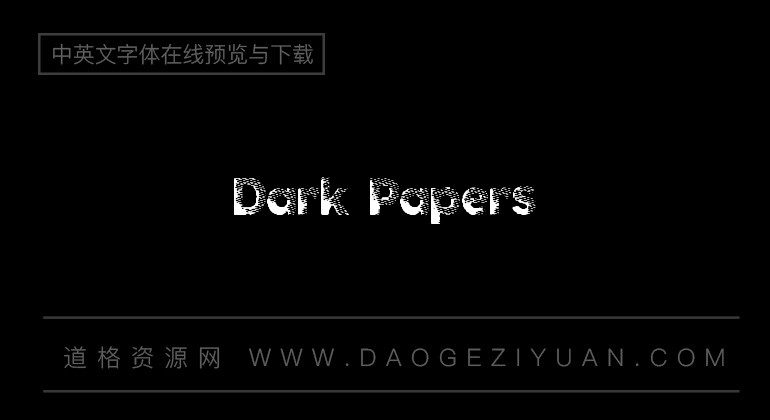
Dark Papers
? Dark Papers 字体是一款具有抽象风格的字体,它有着浓重的视觉冲击力,具有细节丰富的表现形式,可以提供出色的排版效果。它的特点是有着粗犷的线条,并且具有抽象的外观,可以营造出大气的视觉效果。Dark Papers 字体的字形结构清晰,可以满足用户对字体的高要求,它可以用于网页设计、平面设计等多种场景,可以让设计师创作出更加优秀的作品。
Dark Papers是一款非常不错的手写艺术字体,具有很好的视觉感,适合于文化类的宣传设计、商业类品牌的广告和产品包装设计以及个性化文字排版等较多场景。